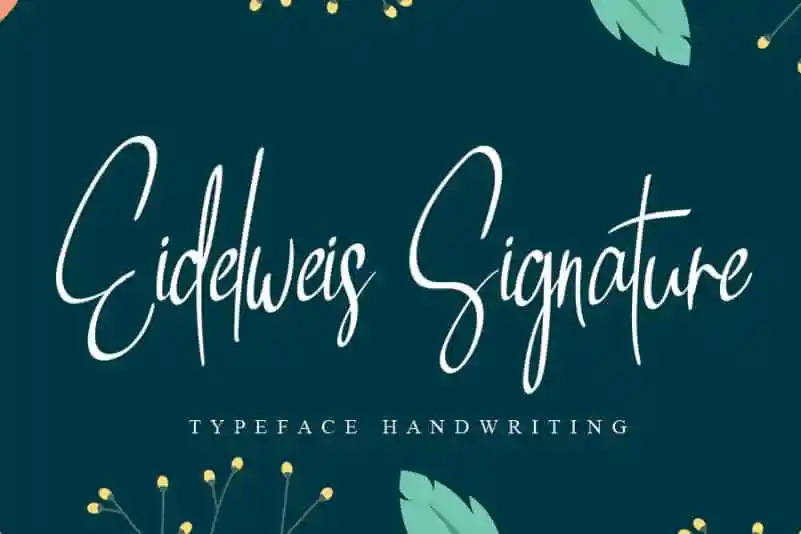
Eidelweis Signature Script Font – Download Grátis
A Eidelweis Signature Script Font é uma elegante fonte escrita a mão que vai encantar qualquer design. Ela é perfeita para aqueles desejando um toque mais casual e delicado, especialmente quando combinada com ideias criativas. Composto de letras finas, essa fonte foi meticulosamente projetada para se tornar uma escolha definitiva. Seu design permitirá que você transforme suas ideias mais audazes e originais em obras ainda mais impecáveis. Eidelweis Signature Script é a escolha perfeita para aqueles buscando um toque suave e elegante, sem perder a personalidade de cada projeto. Ideal para editoriais pessoais ou para trabalhos corporativos que valorizam uma atmosfera acolhedora e única. Através da Eidelweis Signature Script Font, você pode traduzir suas ideias em letras que transmitem força e suavidade, criando textos memoráveis e autênticos.